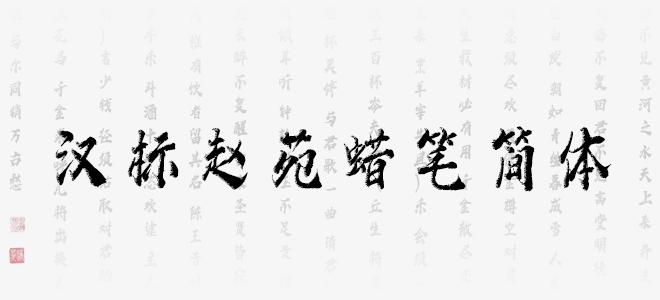
漢標(biāo)趙苑蠟筆簡(jiǎn)體是一款基于漢標(biāo)西紅市首字,軟件再創(chuàng)做的蠟筆感覺(jué)字體,既遒勁有力又不失文雅風(fēng)韻的特色行體。作者自幼學(xué)習(xí)書(shū)法,后臨學(xué)各傳統(tǒng)名派書(shū)法,至成年歷經(jīng)生活滄桑。集數(shù)年所學(xué)及人生感悟融于此款字中,每一筆每一劃都能體現(xiàn)出沉著穩(wěn)重、滄海桑田、剛?cè)岵?jì)又不失傳統(tǒng)書(shū)法之特色。歡迎喜歡漢標(biāo)趙苑蠟筆簡(jiǎn)體的朋友前來(lái)下載使用。
漢標(biāo)趙苑蠟筆簡(jiǎn)體